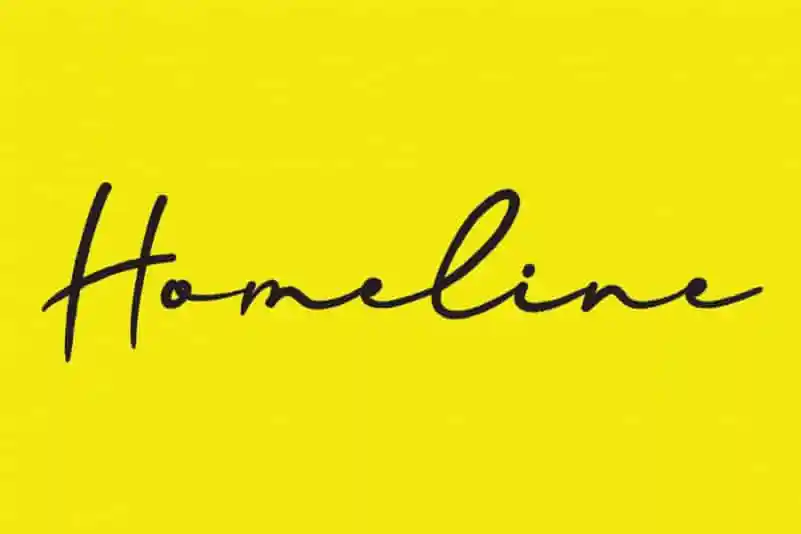
Homeline Script Font – Fonte Grátis
Homeline Script Font
A Homeline Script Font é uma elegante tipografia escrita a mão que encanta por sua relaxada e eterna personalidade. Perfeita para quem busca harmonia no design, esta fonte tem um estilo versátil suficiente para criar convites de casamento incríveis, arte de papelaria brilhante e postagens de mídia social chamativas. Uma característica particularmente atraente é sua versatilidade. Pode ser usada para imprimir belas cartas de aniversário em estilo artesanal ou até mesmo decorar os botões de redes sociais, criando um visual harmonioso e sofisticado. Para aqueles que buscam uma fonte perfeita para combinar vários estilos sem comprometer a qualidade do design, esta é a escolha certa. Homeline Script é mais do que uma font; ela é o elemento que tornará seu trabalho único e marcante, seja em cartões de aniversário delicados ou postagens sociais criativas.